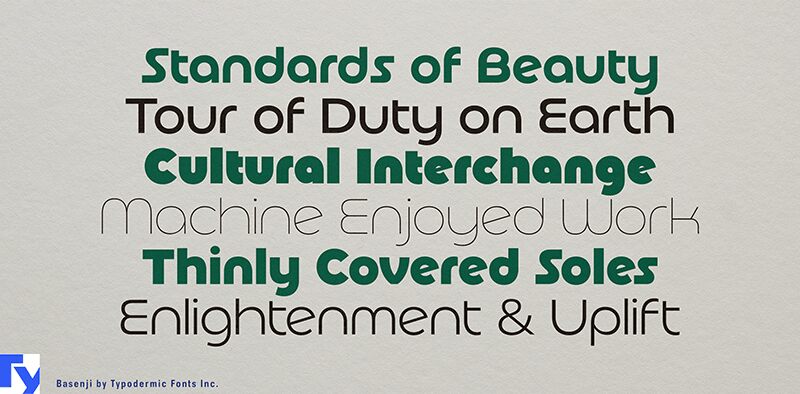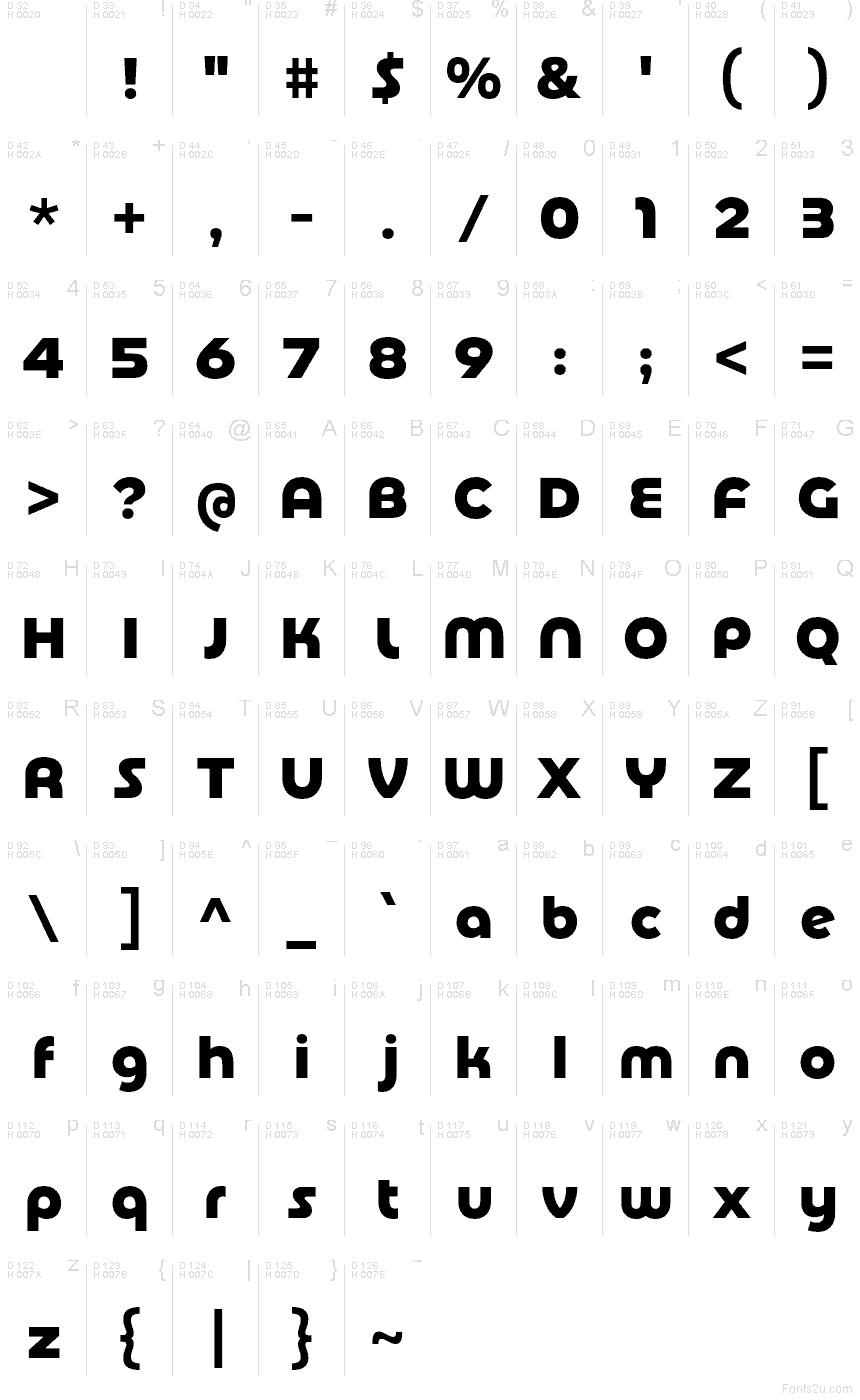
Basenji SemiBold
Basenji s’inspire de la géométrie ludique des classiques des années 1970 tels que Rondo, Pump, Bauhaus et Blippo, tout en les réimaginant avec la précision et la flexibilité qu’attendent les designers d’aujourd’hui. Ses formes arrondies passent aisément d’un texte courant doux et convivial à des titres audacieux et sculpturaux, ce qui la rend tout aussi efficace pour le branding, l’édition ou la signalétique grand format. Ancrée dans le charme rétro mais raffinée pour un usage contemporain, Basenji insuffle la chaleur du passé dans vos flux de création actuels.
Ray Larabie